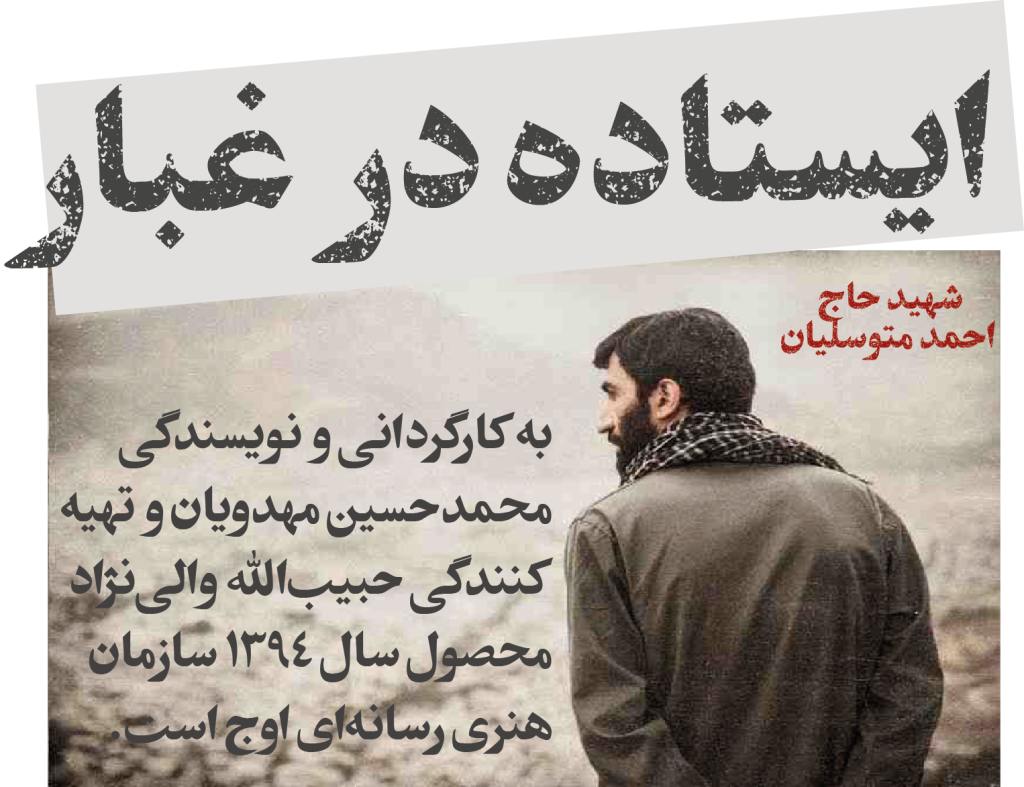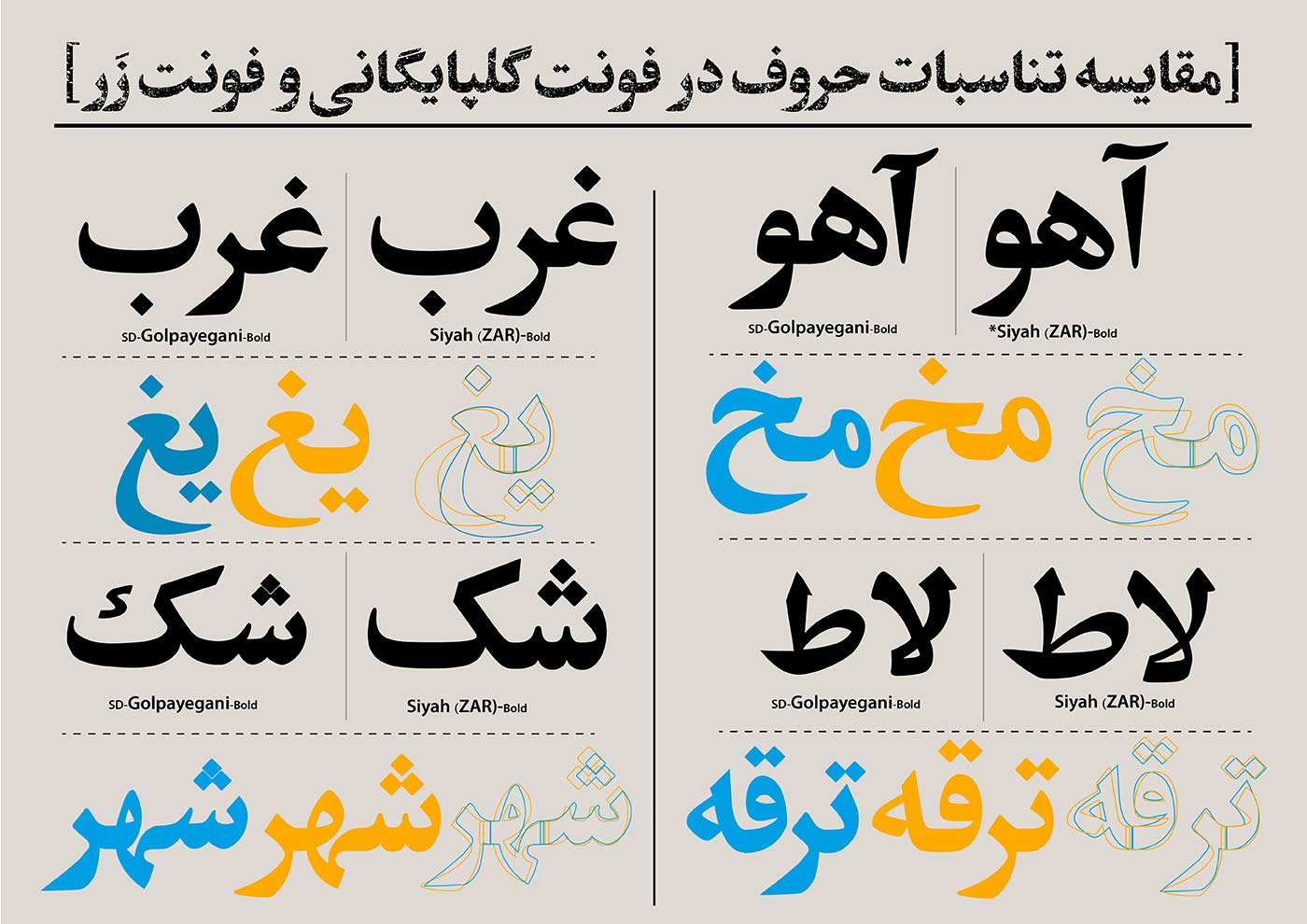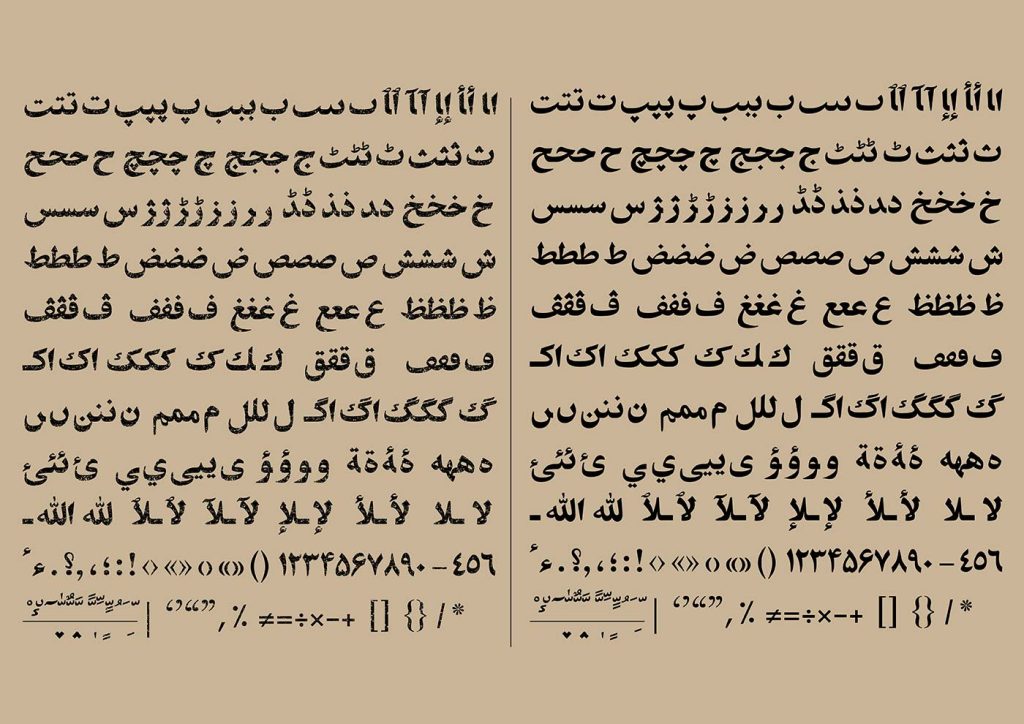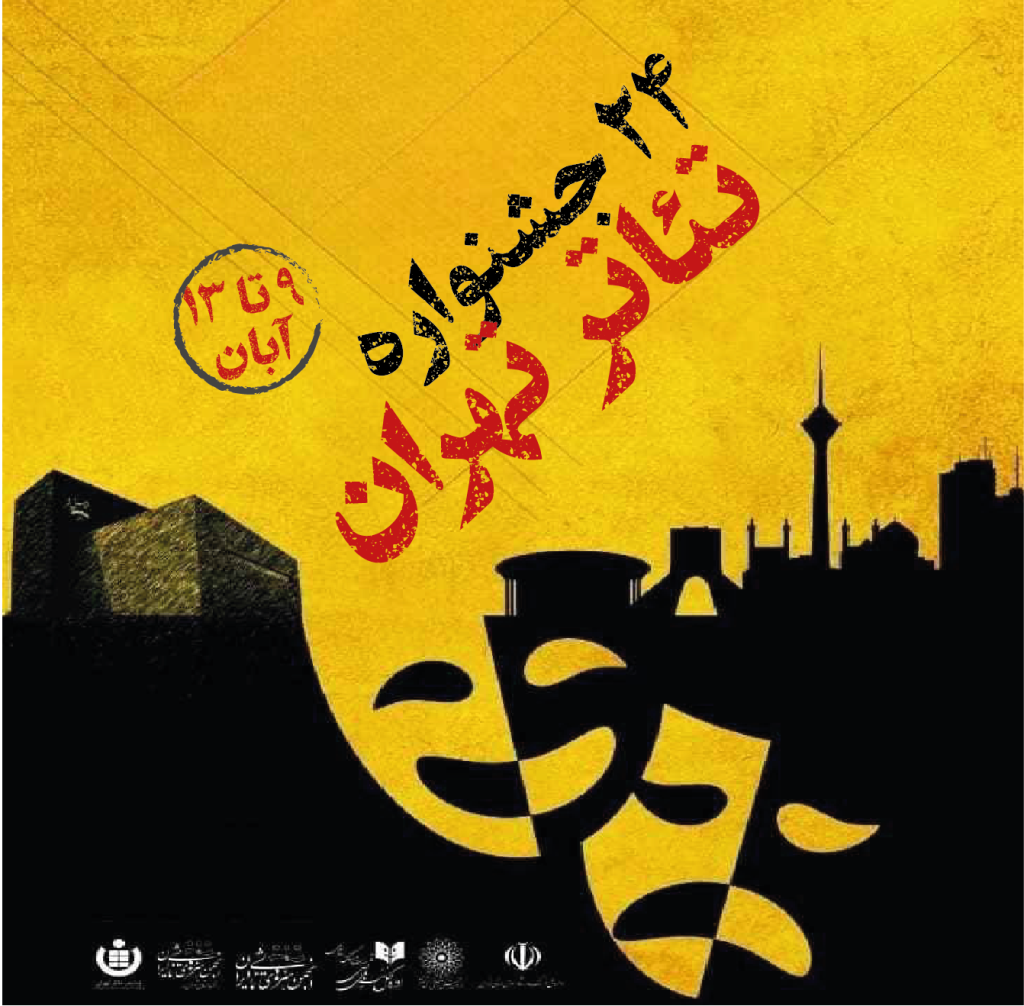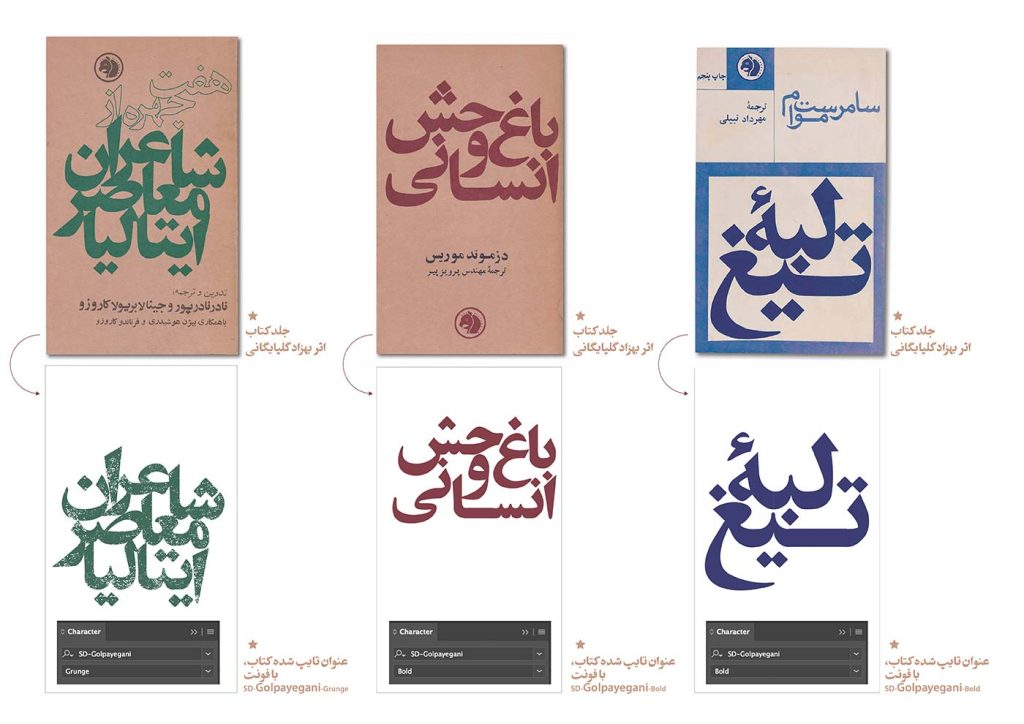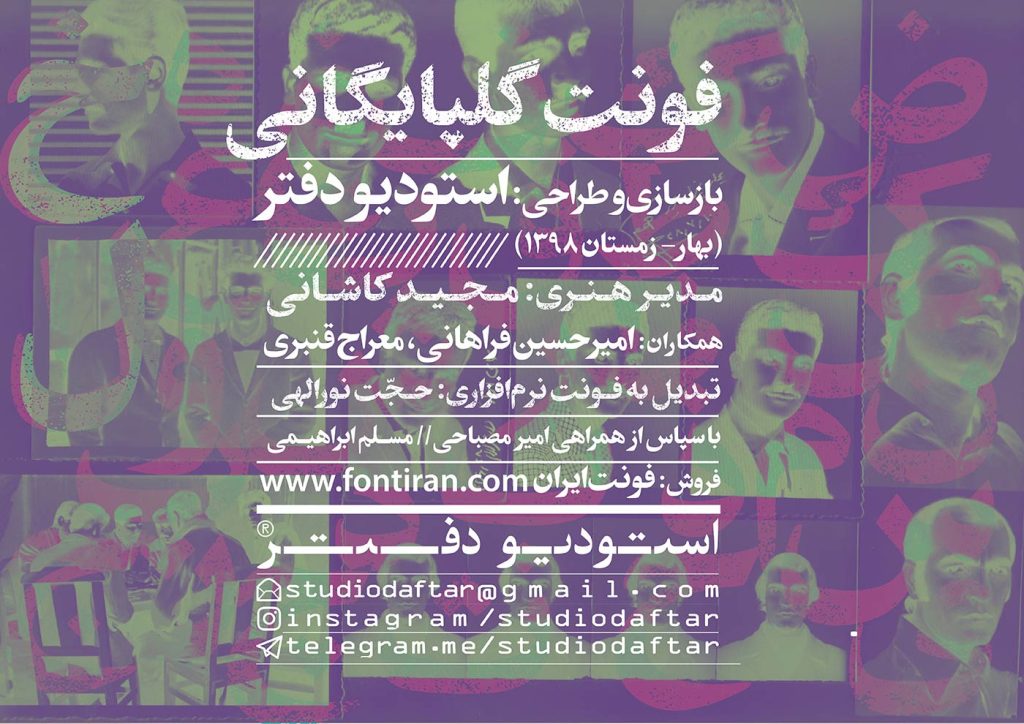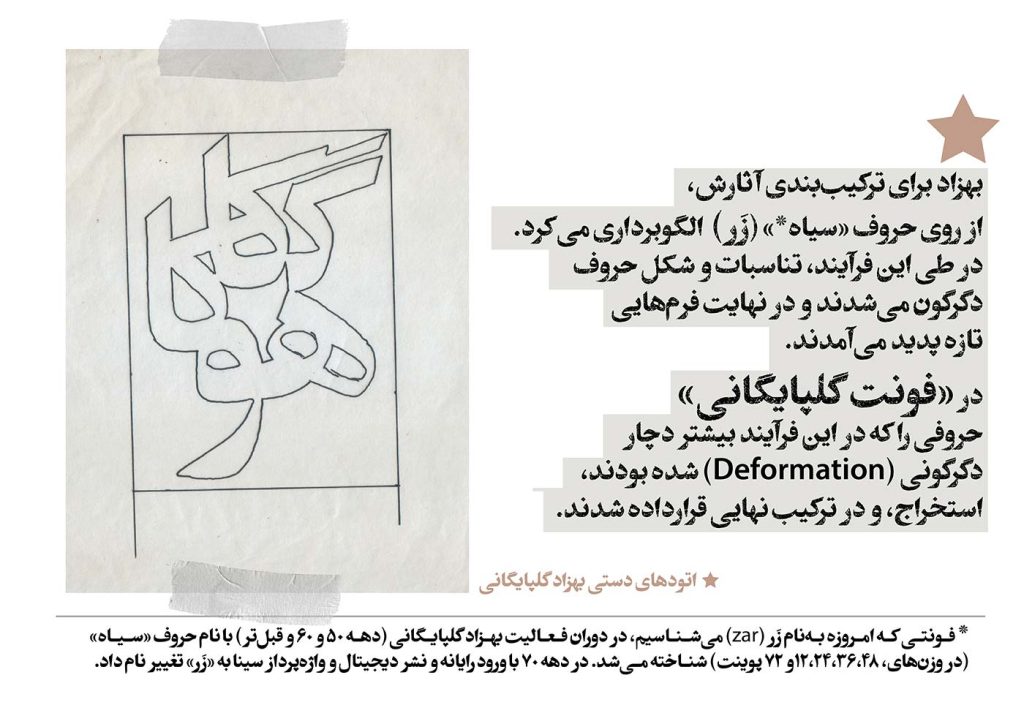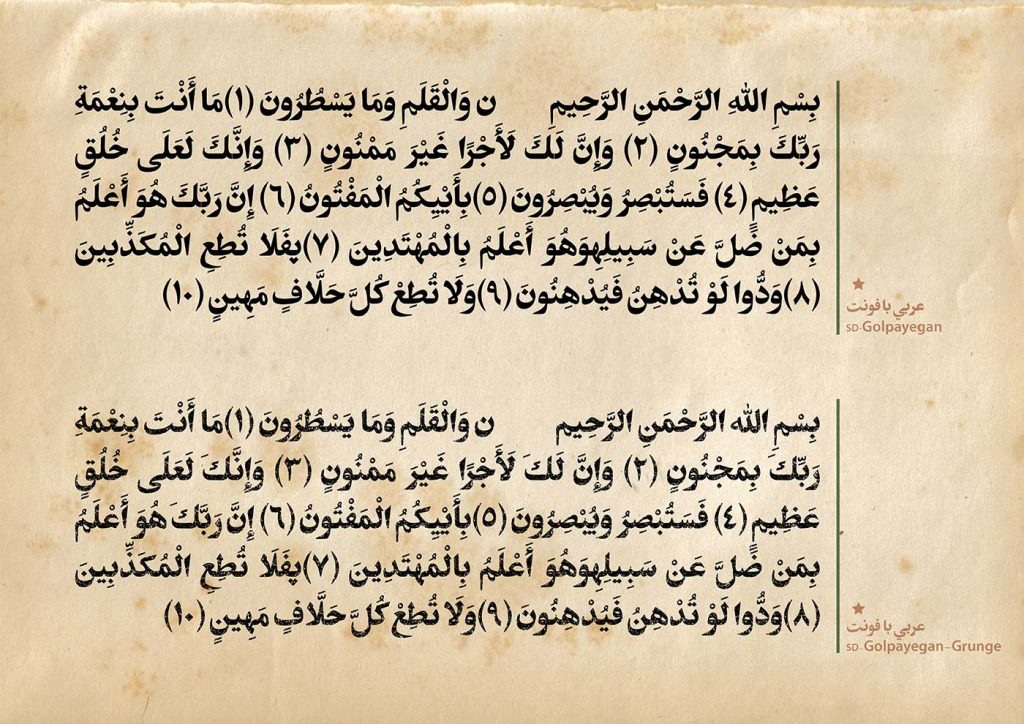
فونت گلپایگانی
فونت گلپایگانی قلمی مناسب برای متون کوتاه و عناوین مطبوعات، جراید ، مجلات و … می باشد . آقای بهزاد گلپایگانی طراح این تایپ فیس طی سالهای فعالیت خویش در «انتشارات فرانکلین»، برای نخستین بار مجموعهای از طرح جلدها را بر پایه تایپوگرافی طراحی کرد.
این قلم دارای شخصیتی با صلابت و استوار می باشد. و برای متون و عناوین که دارای عنصر دیرینگی و سابقه بوده بسیار مناسب می باشد .بی شک در جذب نگاه بینندگان به خود تاثیر شگرف دارد.
اقتباس گلپایگانی از فونت زر(zar)
این قلم با اقتباس از نوع طراحی و شاکله و فرم های فونت فارسی زر ایجاد و بازطراحی شده است. در طی این فرآیند طراحی، تناسبات و شکل حروف تبدیل به دگرگونی و دگردیسی شده که نتیجه آن پدید آمدن فرمهایی تازه است که منجر به تولد این قلم شده است.
گلپایگانی و دو استایل مختلف
این قلم با دارا بودن دو استایل ساده و بافت بازسازی شده ( مناسب متون قدیمی و انتقال احساس دیرینگی و … ) مناسب متون و عناوین از صنعت چاپ تا دنیای دیجیتال و وب می باشد. کاربرد آن بیشتر در محتواهایی با فضای رسمی و کلاسیک است.
گلپایگانی هم چنین با دارا بودن اعراب و علائم نگارشی از زبان عربی نیز پشتیبانی می کند . در زیر تصاویری نمونه از این قلم زیبا برای شما دوستان عزیز آماده و مهیا شده است. بی شک این تایپ انتخابی بسیار مناسب برای طراحی های شما است.
2 استایل
نوشتههای آثارش را از روی حروف «سیاه» (زَر) الگوبرداری میکرد. در این فرآیند ، تناسبات و شکل حروف دگرگون و در پایانت فرمهایی تازه تولید می شدند. این قلم دارای ویژگی حفظ اصالت در عین دارا بودن پویایی و تازگی خود جهت جذب نگاه خوانندگان و بینندگان به خود می باشد.
جهت بازسازی و تازه سازی در فونت گلپایگانی حروف و گلیف هایی که در این فرآیند بیشتر دچار دگرگونی (Deformation) شده بودند، استخراج، باز طراحی و در ترکیب نهایی قرارداده شدند.